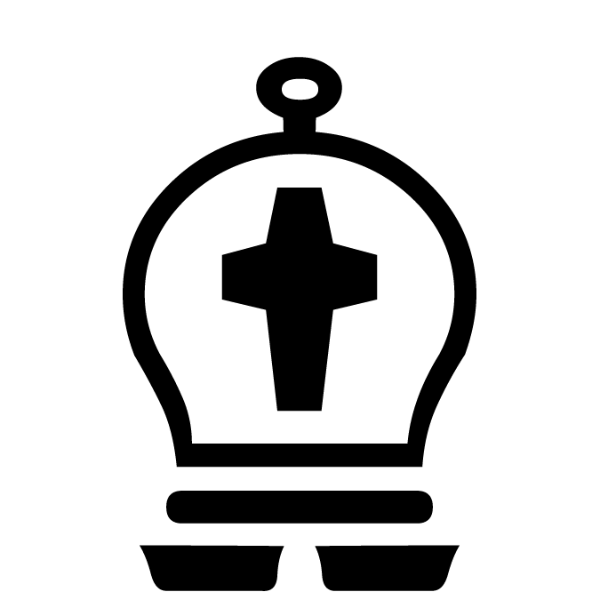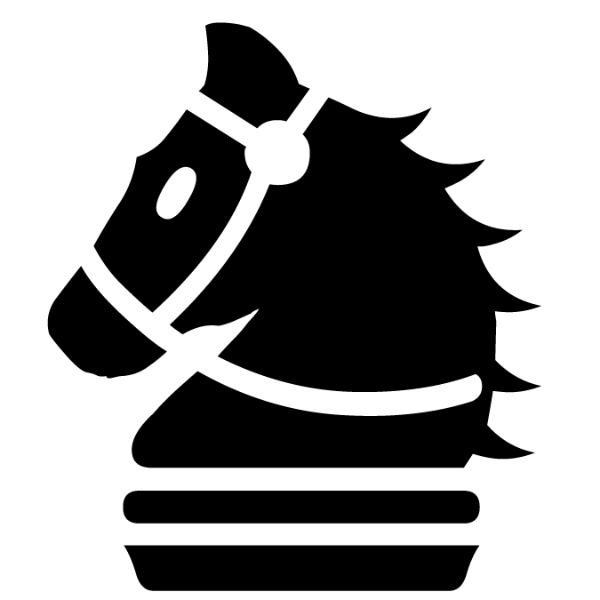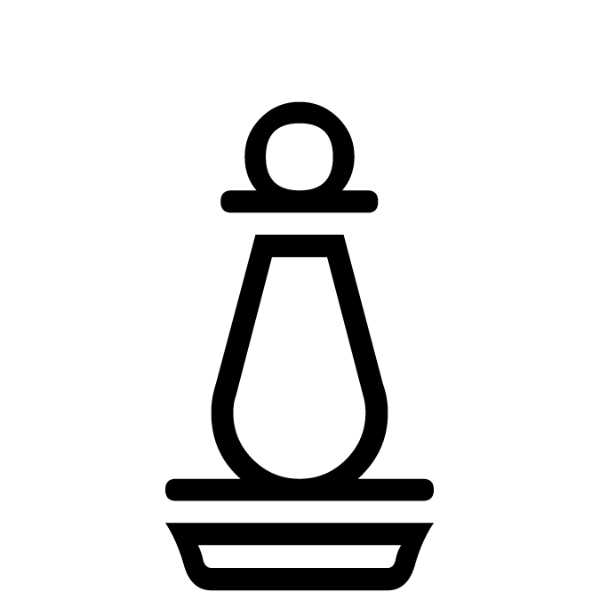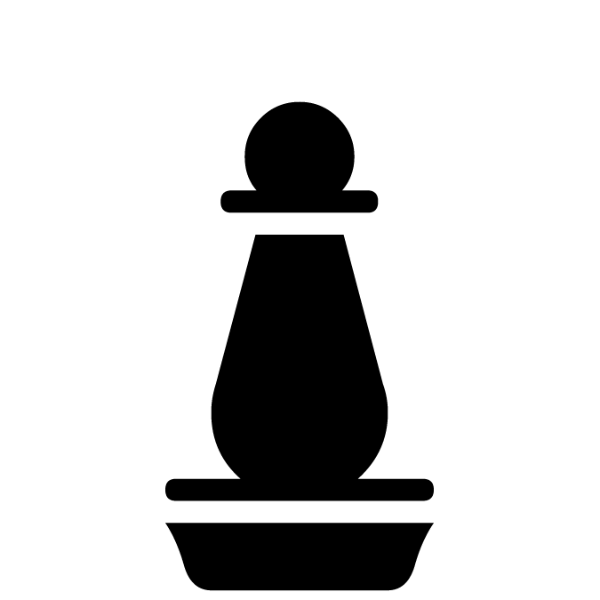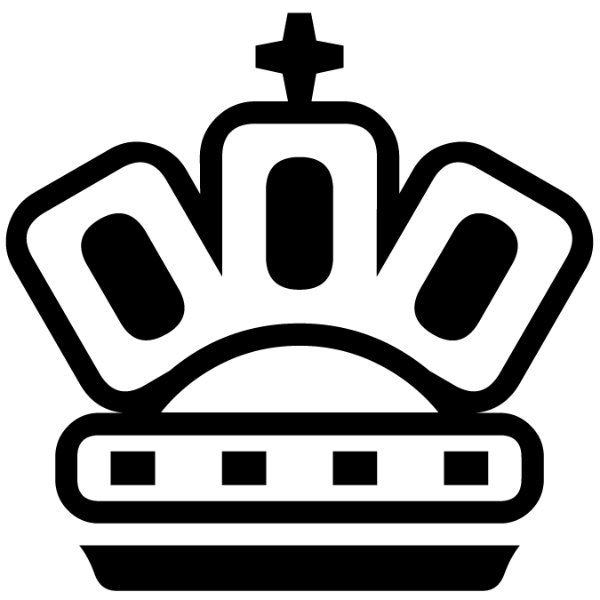
La Fuente Chess Magnetic destaca por sus diseños únicos y detallados en las piezas de ajedrez. El Rey se distingue por sus tres secciones inferiores, la Reina por las esferas ornamentales en sus puntas, y la Torre por su estructura robusta y prominente.
Juego de Ajedrez con la Fuente Magnetic: